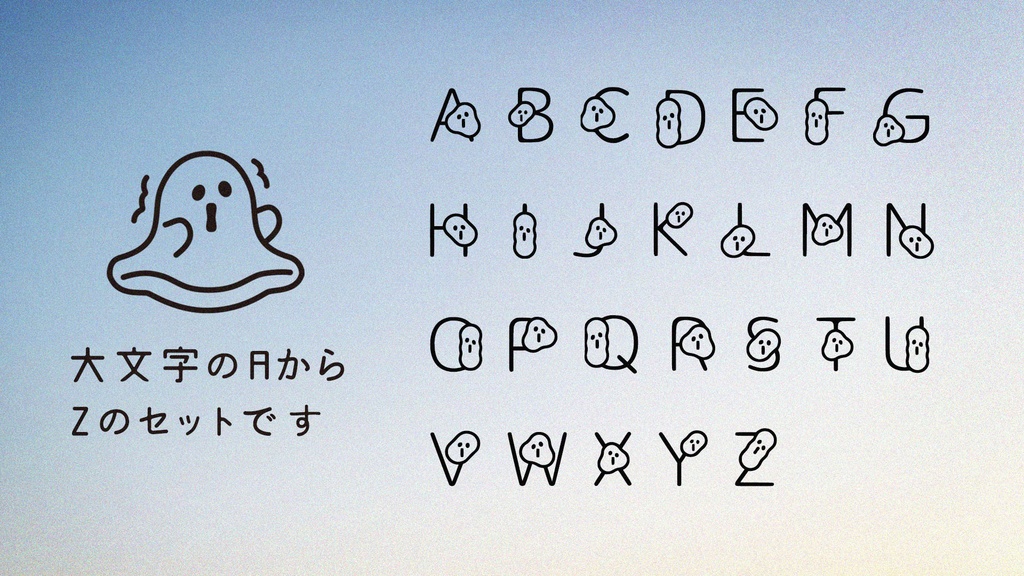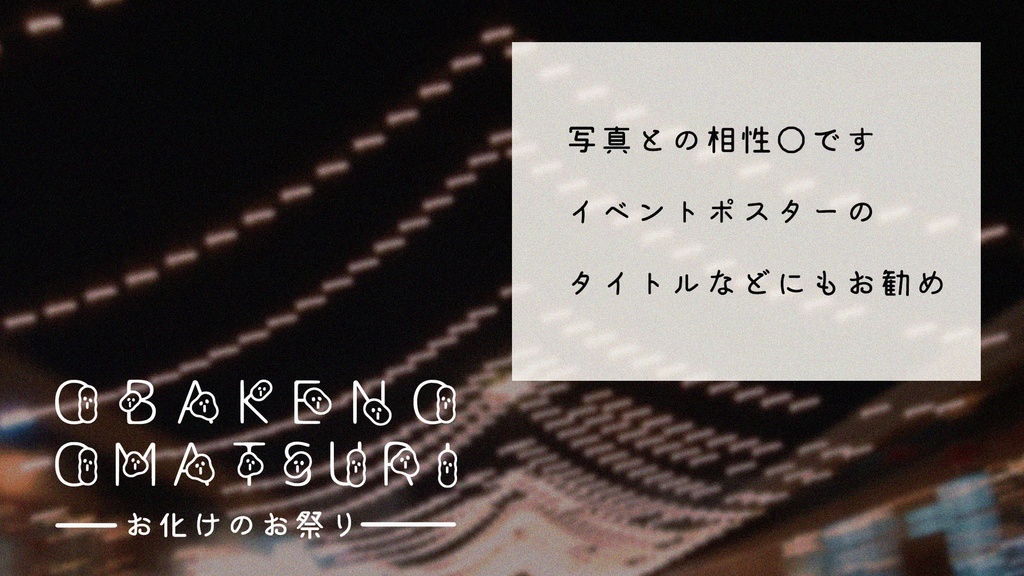
お化けがいっぱいのフリーフォント
お化けがいっぱいのフリーフォント【英字フリーフォント/Free Font】 商用&個人で使用できる英語フォントです。 同人誌やZINE、雑誌、ポートフォリオ等にお使い頂けます。 【内容】 A~Zまでの大文字 ※数字、小文字は含まれておりません 以前作ったフォントが好評なようなので、 またまたホームページのリニューアル記念で配布いたします○ 著作権は放棄していませんので、以下の規約を守ってお使い下さい。 /////////// ・フォントデータの複製、改変、再配布、再販売などは禁止させて頂きます。 ・使用する際に一部改変頂く事は問題ございません(一部色を変える、等) ・こちらのフォントを使用した際のトラブル(PCの誤作動やウィルス感染、それに伴う故障など)については責任を負いかねますのでご了承下さい。 ・反社会的な内容、R18な作品、差別を助長するような表現、暴力的な表現の作品・広告等への使用は禁止させて頂きます。 ○商用でお使い頂く際にも、連絡は必要ありません。 製作者 2021(c) Miki Kuri twitter/@umaimesitaberu https://illustration.kuristudio.work/